왕은실 캘리그라피.3_다양한 붓과 도구들이 표현한 글꼴
이번 칼럼에서는 다양한 도구들을 이용한 글씨들을 살펴보도록 하겠습니다. 잘 아시겠지만 붓에는 종류가 굉장히 많습니다. 양털, 닭털, 말털, 족제비털, 곰털, 수달털, 토끼털 등 다양한 털의 붓이 있습니다. 글자는 사용하는 붓털 길이와 크기에 따라 질감이 달라지지만, 붓 크기에 따른 글씨 면적이 가장 크게 변화하는데요. 막상 글자를 다양하게 쓰려면 초보자에게는 붓만 가지고는 어려울 수 있습니다. 그래서 이번 글에서는 우리 주변에 있는 흔한 도구들을 이용해 화선지 위에 쓰면 어떠한 글자들이 나오는지 하나씩 확인해보도록 하겠습니다.
1. 면봉
첫 번째 주인공은 목욕탕 또는 화장대 위에서 흔하게 볼 수 있는 면봉입니다. 이 면봉에 먹물을 묻혀 화선지(연습지)에 써보도록 해보죠. 아래 글씨는 썼다기 보다 찍어서 글자를 만들었다고 볼 수 있는데, 면봉은 끝이 동그랗기 때문에 그 특성을 살리기 위해 한 점씩 찍어서 ‘면봉’이라는 글자를 만들어 보았습니다. 왜 쓰지 않고 만들었을까요? 쓰기도 하지만 다양한 모양을 만들기 위해서는 만들기부터 시작하는 것도 좋습니다. 획을 쓰기 위한 가장 기본적인 선부터 글꼴의 구성이 중요하지만, 쉽게 시작해보는 것도 하나의 방법입니다.
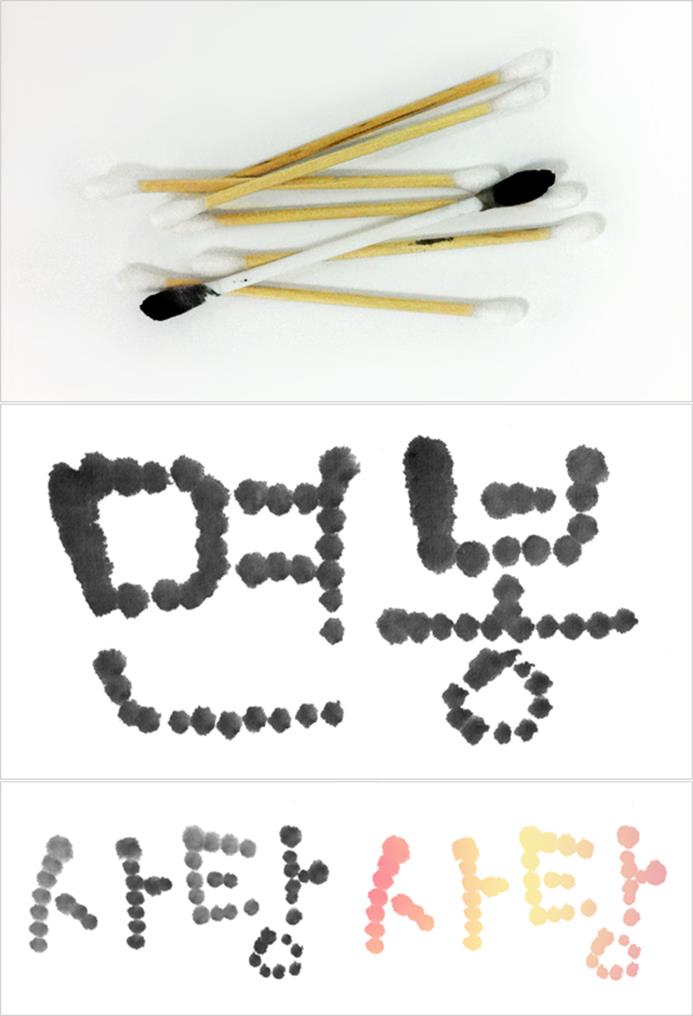
이렇게 실험한 질감으로 연상되는 단어를 찾아 연결해 쓰면 그 글자의 느낌을 한층 더 살려낼 수 있습니다. 그리고 ‘면봉’이라는 글자를 써보고 연상된 단어 ‘사탕’을 다양한 먹색으로 써보았습니다. 검정색이 사탕 느낌을 주지 않는다면 포토샵을 활용하여 색을 보정할 수도 있습니다.
2. 빨대
음료수를 마실 때 사용하고 남은 빨대들을 활용할 수도 있는데요. 먹물을 묻히기도 공기압으로 먹물을 머금으면서 써보았습니다. 아무래도 검정색만으로 쓰기에는 어두운 느낌을 많이 주기 때문에 저는 물을 먼저 머금었습니다. 빨대 끝 부분을 엄지손가락으로 막았다 놓았다 하면서 물을 머금고, 다음에 먹물을 조금 섞어 머금은 후에 화선지에 빨대 끝에 있는 엄지손가락으로 물을 조절하여 글씨를 쓸 수 있습니다. 한번 머금은 먹물은 금방 빠지기 때문에 두 글자를 쓰는 동안 서너 번은 위와 같은 방법을 반복해야 합니다. 먹물과 물의 양에 따라 먹 색이 다양하게 표현되며 우연성도 함께 동반되기 때문에 재미있는 효과를 기대할 수 있죠.
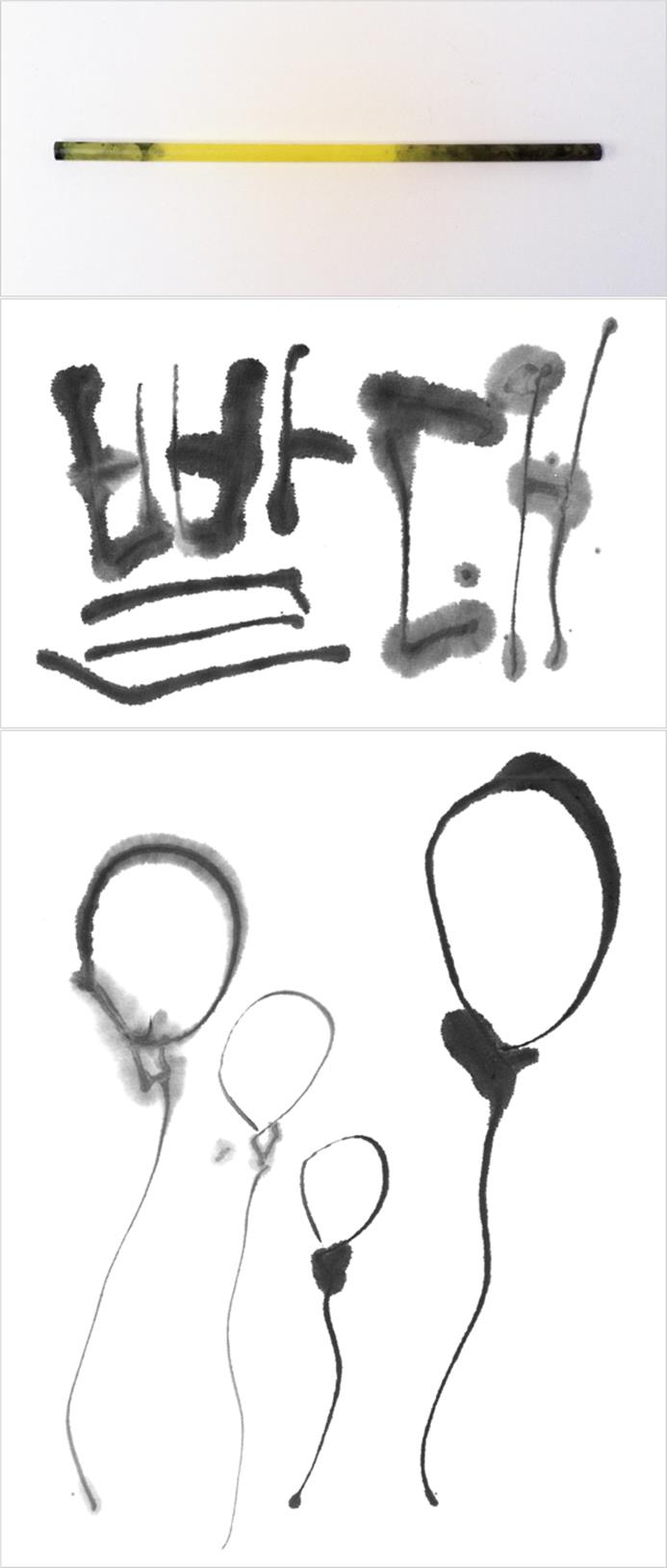
빨대를 활용해 풍선도 그려보았는데요. 글씨도 쓰지만 강략을 특별히 주지 않아도 빨대에 머금은 물과 먹물의 양을 잘 조절하면 다양한 풍선 모양을 나타낼 수 있습니다. 이러한 먹그림들은 디자인 요소로 사용해도 손색이 없겠죠.
3. 수세미
최근엔 다양하고 예쁜 수세미가 많이 만들어져 흔하게 볼 수 있었던 초록수세미를 찾아보기 어려워지기도 했습니다. 저는 초록수세미를 벼루 닦을 때 사용하곤 하는데, 그렇게 사용하다 남은 수세미들을 크기 별로 잘라 글씨를 쓸 때도 있습니다. 아래 ‘수세미’라는 글자는 수세미를 반으로 접어 먹물을 묻히고 사선으로 속도를 내면서 써본 것입니다. 의외로 강력한 느낌의 이미지로 표현되었죠. 꼭 이런 방법만 있는 건 아닙니다. 수세미로 쓰면 항상 이런 느낌만 나오는 것도 아닙니다. 면봉처럼 찍어서 표현했을 때는 또 다른 느낌을 낼 수 있고 먹물 양에 따라 조금씩 달라질 수 있습니다.
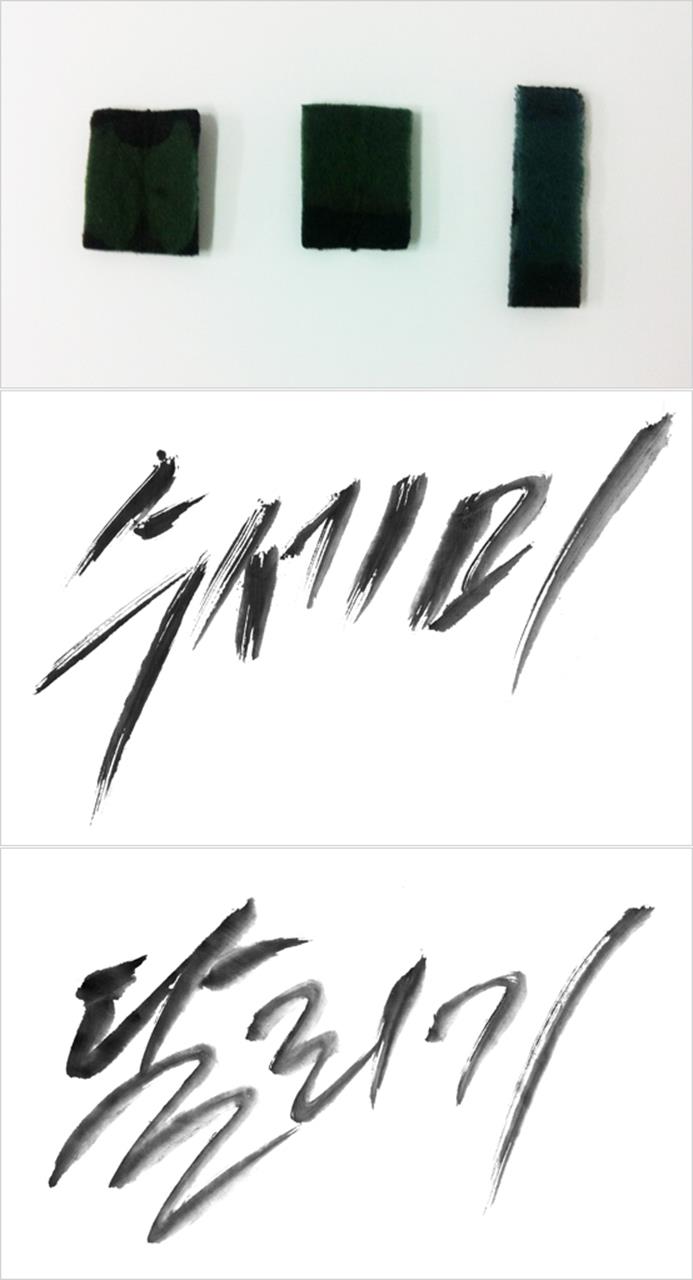
‘수세미’ 글자를 표현했던 방법으로 ‘달리기’를 써보았습니다. 글자와 표현 방법이 잘 어울려 보이네요. 위 ‘수세미’ 글씨보다 물을 더 많이 첨가하여 먹색이 조금 더 다양하게 보이도록 작업해보았습니다.
4. 펜촉
저는 알파벳 글자를 쓸 때 사용하는 만년필 펜촉들을 갖고 있는데, 영자 필기체를 사용할 때 보다 먹물을 이용할 때가 더 많습니다. 아래 첫 번째 ‘Calligraphy’ 글자는 두 펜촉 중에 얇은 펜촉을 이용해 A4 용지에 쓴 것인데요. 영어를 쓸 때 사용하는 펜촉이라 캘리그라피를 영어로 써보았습니다. A4 용지이기 때문에 번지지 않고 깔끔하게 표현되었습니다.
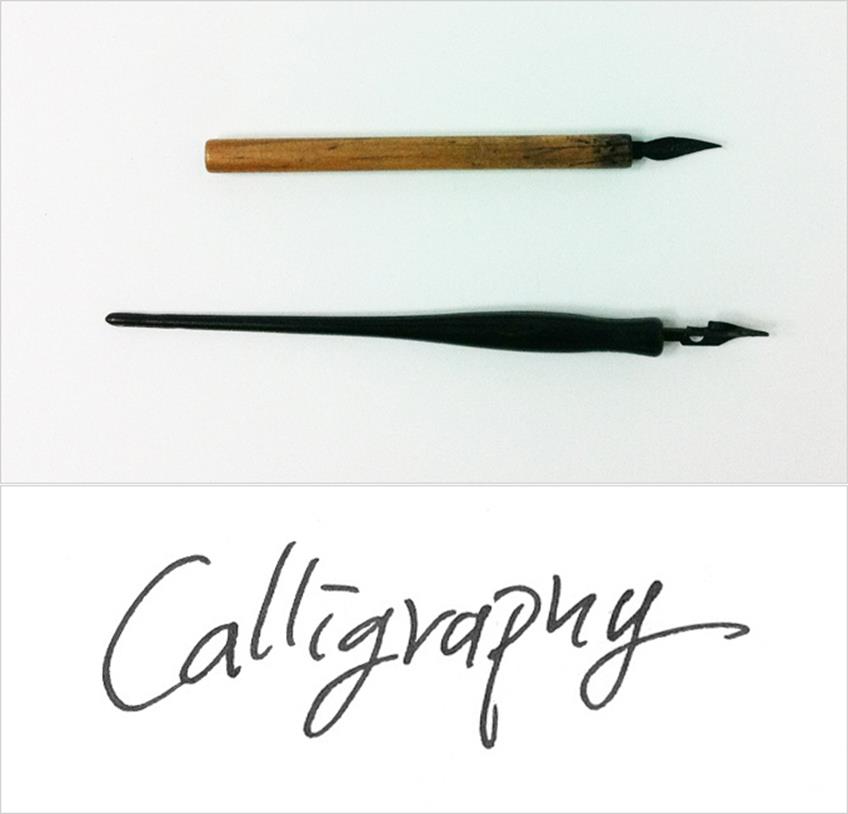
아래는 넓은 펜촉을 이용하여 A4 용지에 써 본 것입니다. 먹물을 한번 묻혔기 때문에 ‘y’를 쓸 때쯤에는 먹물이 닳아 흐리게 표현되었습니다. 저는 먹물이 꼭 모두 균등한 톤으로 써지지 않고 점점 흐려지면서 먹색이 변하는 것도 좋아합니다. 그 아래 글자는 화선지에 얇은 펜촉을 이용해 써본 것인데요. 먹물은 A4 용지보다 화선지에 더 잘 번지기 때문에 털로 쓴 것과 같이 보송보송한 느낌으로 표현됩니다.
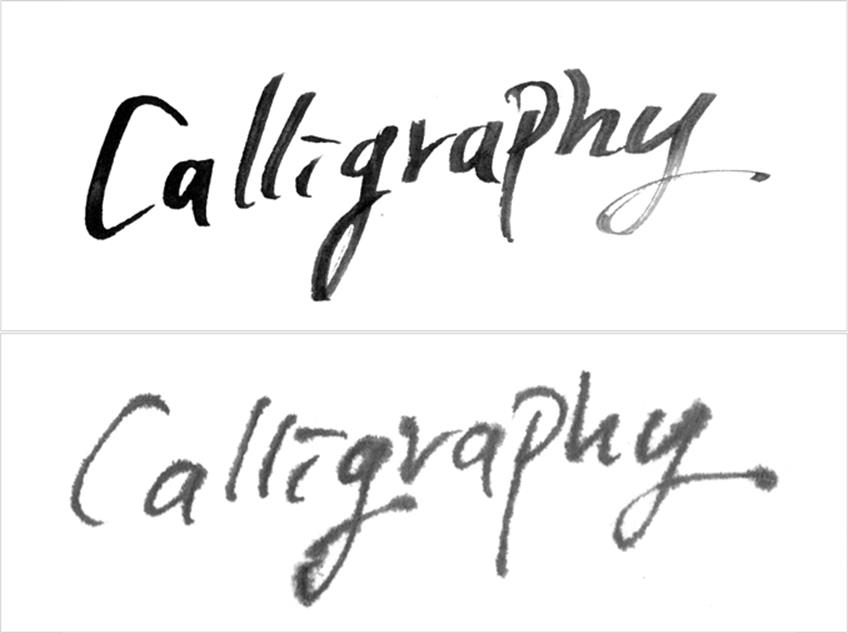
5. 나무젓가락
나무젓가락은 역시나 우리 주변에서 흔하게 구할 수 있는 도구 중 하나입니다. 아래 그림을 보면 알겠지만 나무젓가락은 여러 방법으로 활용할 수 있습니다. 부러뜨린 것도 있고, 연필처럼 깎아서 사용하기도 하고, 한 쌍을 그대로 사용하기도하며, 한 개만 사용할 때도 있습니다.
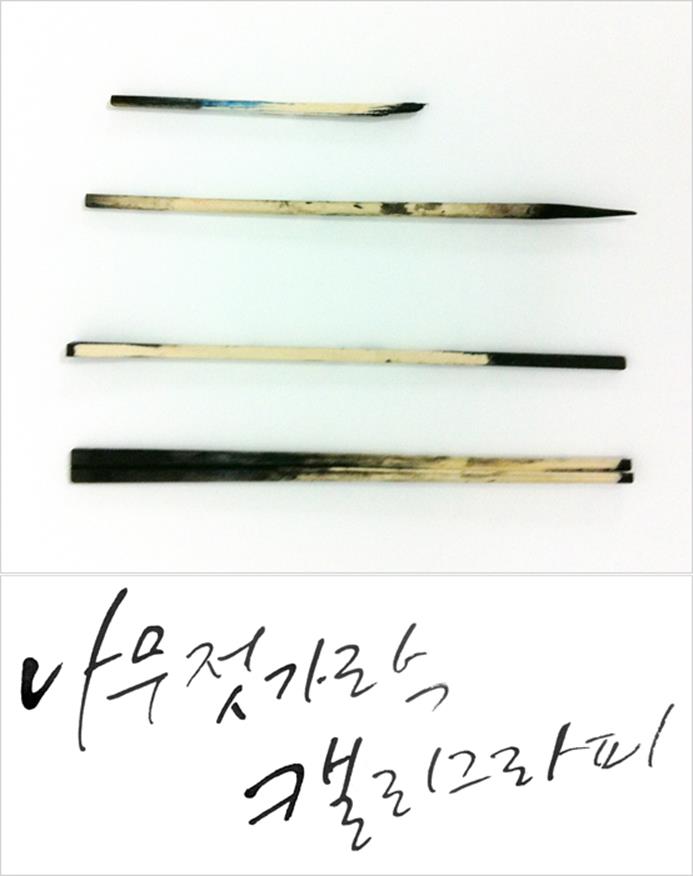
위 그림은 깎아서 사용한 나무젓가락과 A4 용지를 활용해 쓴 글씨입니다. 번짐이 많지 않기 때문에 먹물이 많이 묻은 곳은 그대로 말라서 두껍게 표현되고 먹물이 떨어지게 되면 글자는 얇은 선으로 써집니다. 위 글씨를 보게 되면 ‘나’와 ‘캘’은 굵게 표현된 것처럼 글씨를 강조 할 때에는 한 글자를 쓸 때마다 먹물을 묻혀 글씨를 써야 합니다.
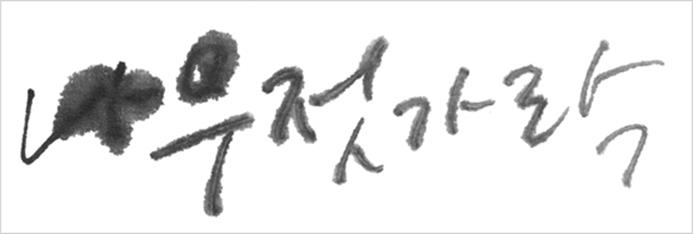
위 예시는 화선지 위에 나무젓가락을 이용해 글씨를 써본 것입니다. 화선지는 많이 번져 보이는데, ‘나무’ 부분이 가장 많이 번졌다는 것은 물이나 먹이 많이 묻어 있었다는 것을 의미합니다. 물을 함께 사용했기 때문에 글씨가 까맣게 되지 않고 어느정도 글씨를 알아 볼 수 있게 작업 되었습니다.
6. 닭털붓
이 도구는 흔하게 구할 수 있는 붓은 아니지만, 필방에서는 구입이 가능한 도구입니다. 아래 붓은 닭털로 만든 것인데 우리가 흔히 알고 있는 서예붓과는 다른 모양을 하고 있죠. 특히나 끝부분이 일반적인 붓처럼 모여있지 않고 닭이 푸드득 날아다니는 느낌처럼 뻗어 있습니다. 이 붓을 이용해 글씨를 써보면 어떻게 표현될까요?
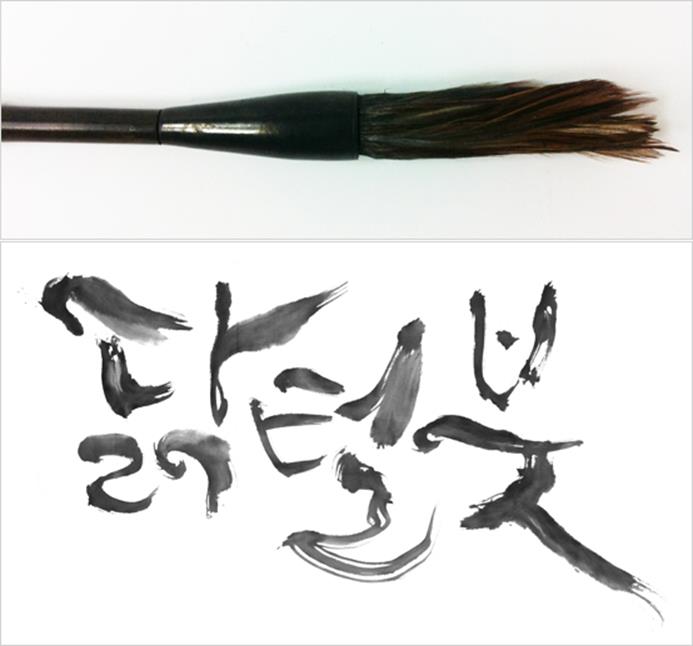
위 그림은 털 끝이 잘 모아지지 않는 닭털붓을 최대한 모아서 써보려고 노력한 것입니다. 시작하는 부분은 동그랗게 모아서 시작하고 끝나는 획들은 그대로 갈라지는 결을 사용하였습니다. 글씨도 닭이 푸드득 날아가는 모습처럼 써지는 것이 특징입니다.
지금까지 여섯 도구를 활용하면 어떤 글자가 써지는지 알아보았습니다. 다시 한번 강조하지만 위에 소개한 여섯 가지 도구를 활용해 쓸 때 그 방법을 다양하게 응용하면 열 가지든, 60가지든 다양한 느낌의 글자를 표현할 수 있습니다. 이렇게 강조하는 이유는 다양한 표현기법으로 새로운 글자들의 꼴을 만들어 가며 캘리그라피의 독창성을 찾길 바라는 마음이 크기 때문입니다.
최근에는 컨셉이 담긴 캘리그라피 보다는 그냥 붓글씨로 써놓은 캘리그라피가 많이 보여 안타까운 마음이 큽니다. 글꼴과 도구 연구를 통해 컨셉이 확실하고 용도에 맞는 캘리그라피가 사용되기를 바랍니다. 다음 칼럼에서는 간단하게 그림을 그리는 방법에 대해 설명하고 글씨와 그림의 조화로운 배치에 대해 알아보도록 하겠습니다.